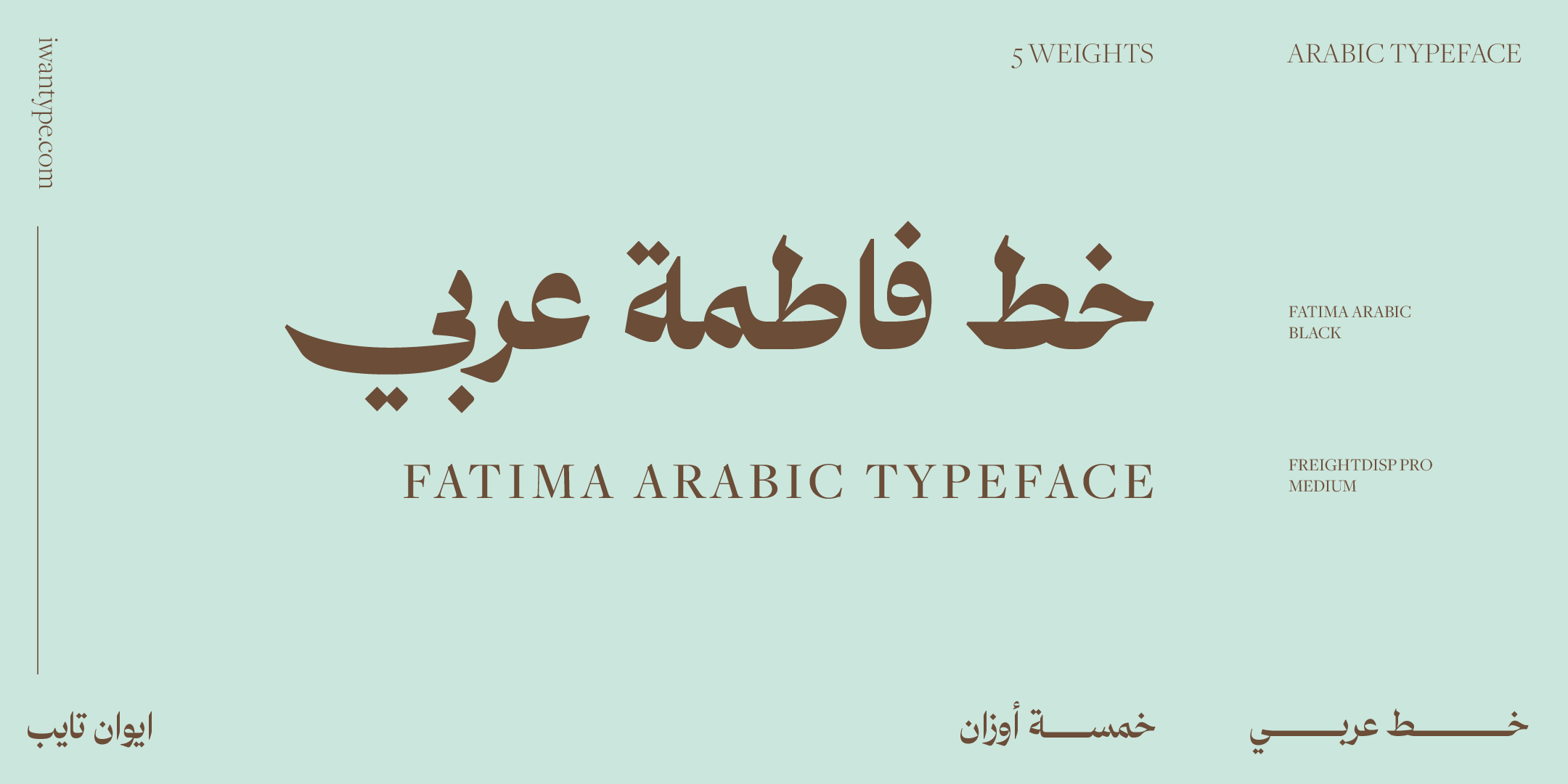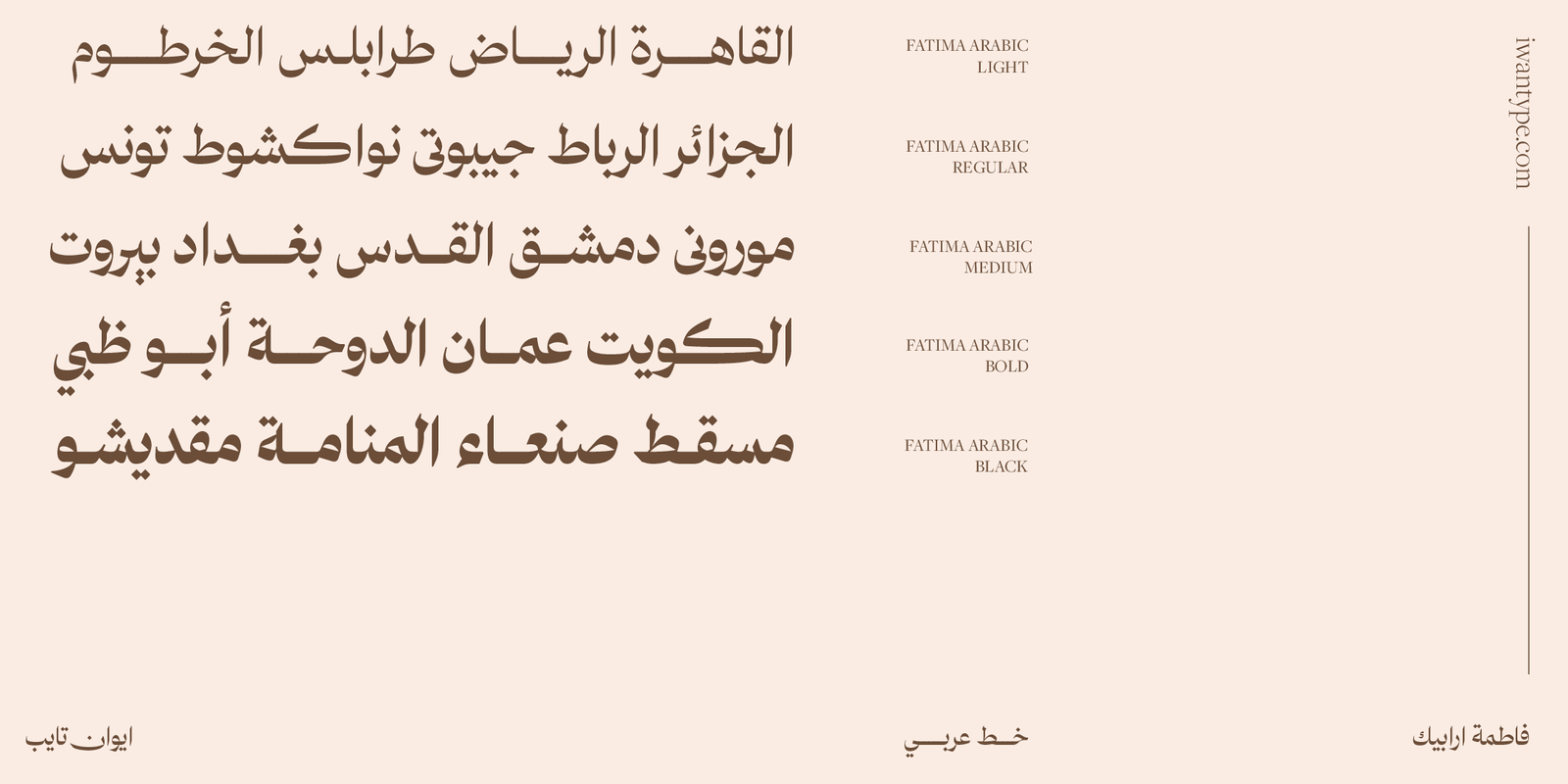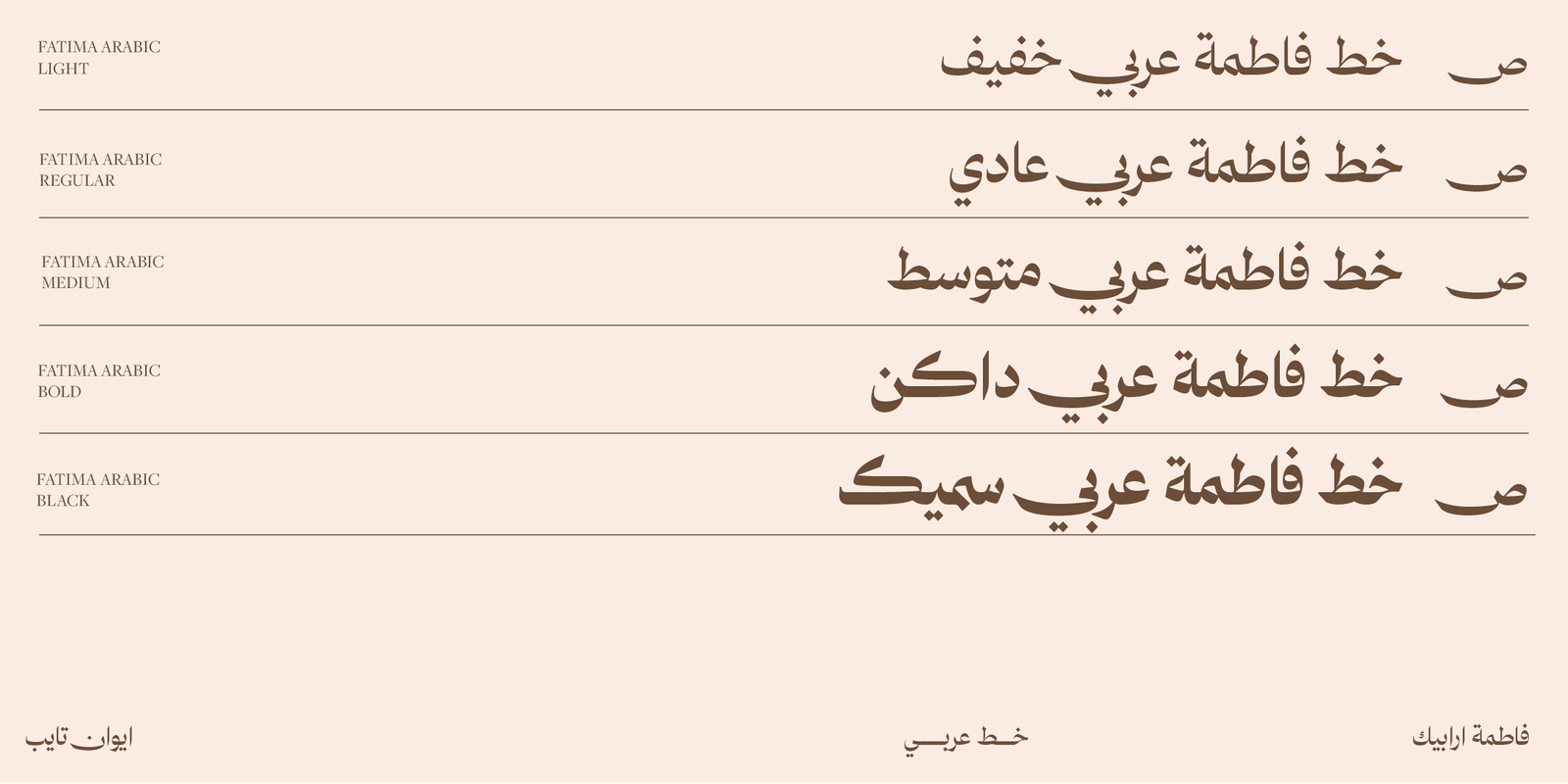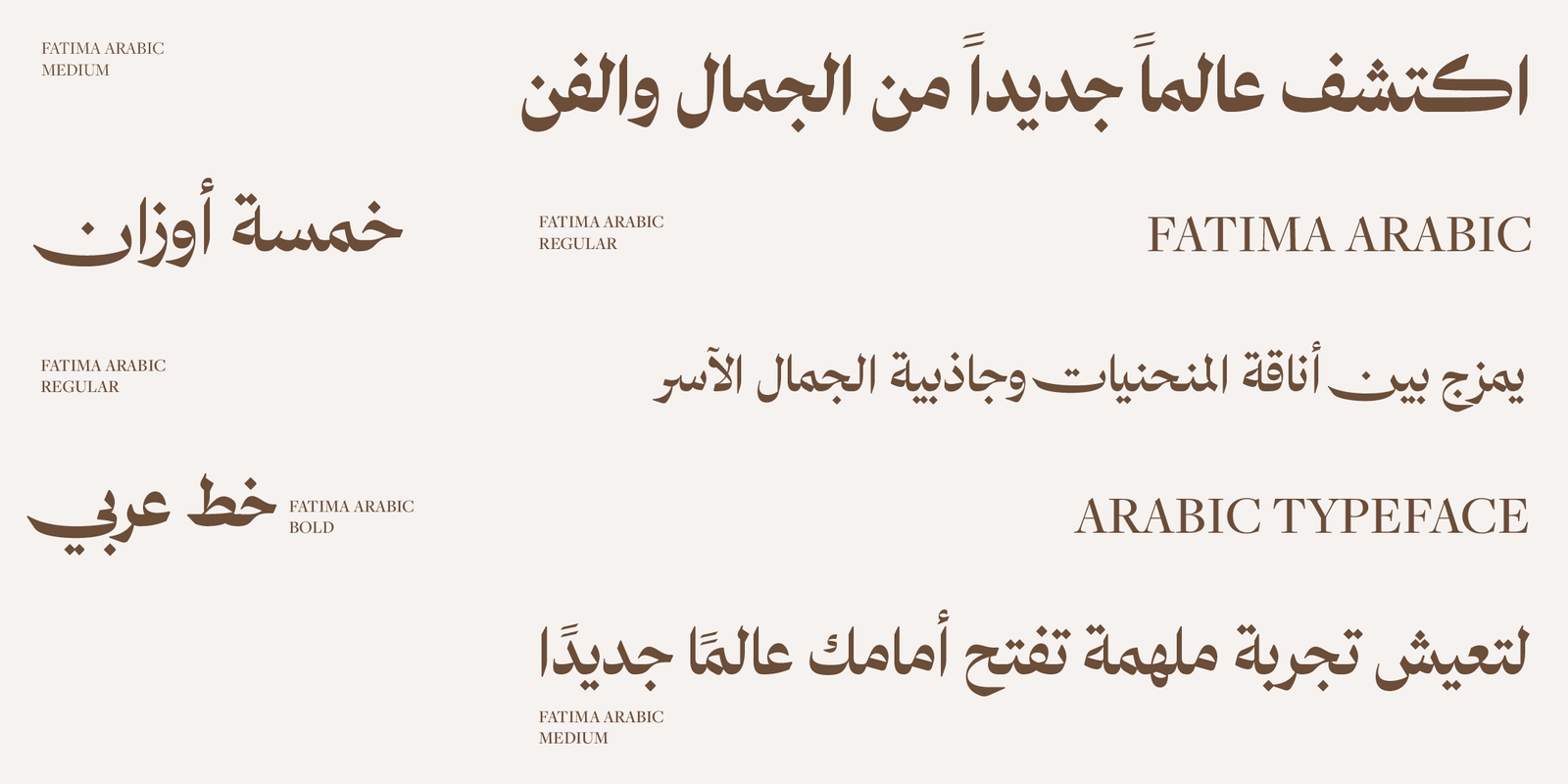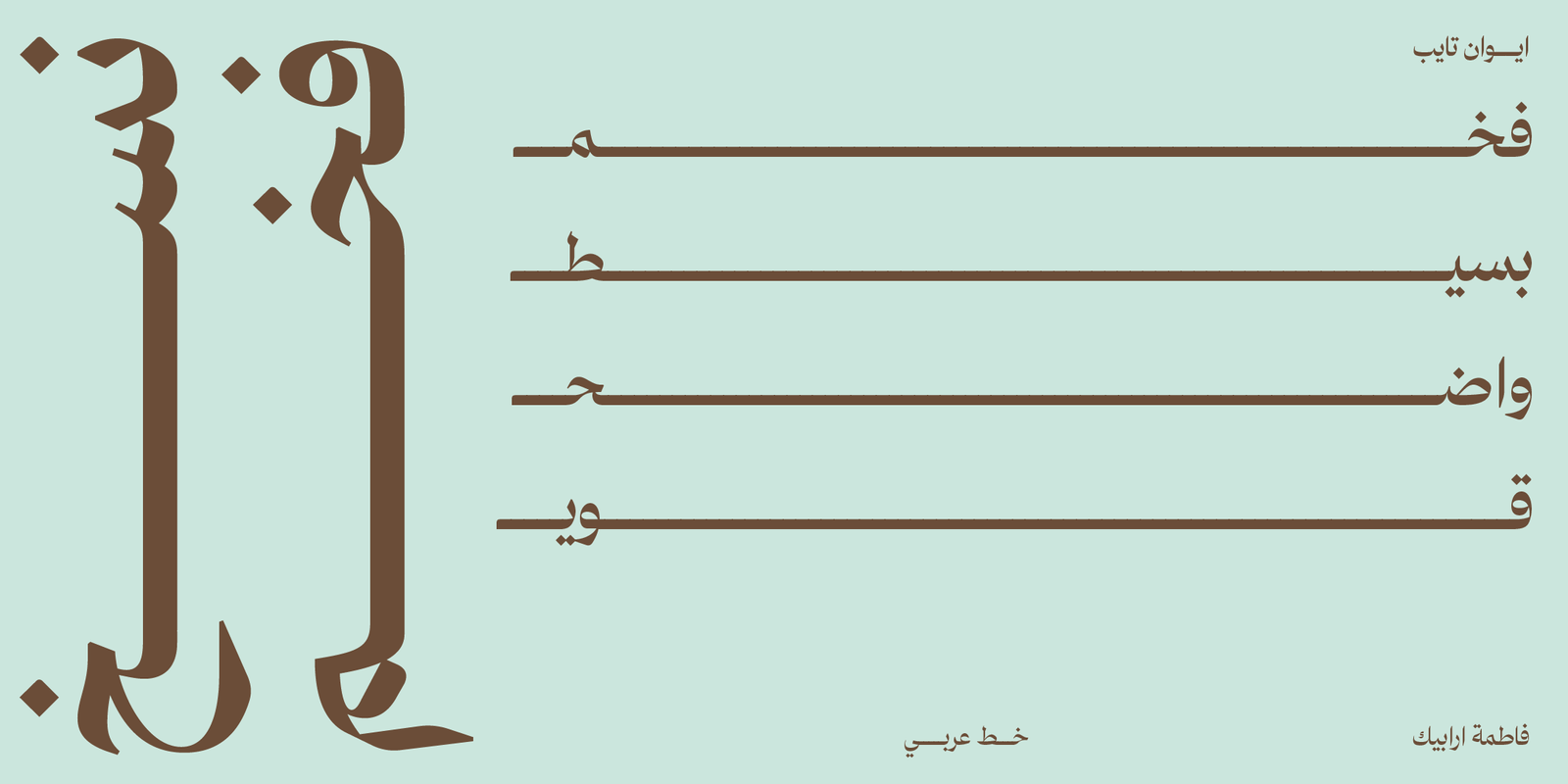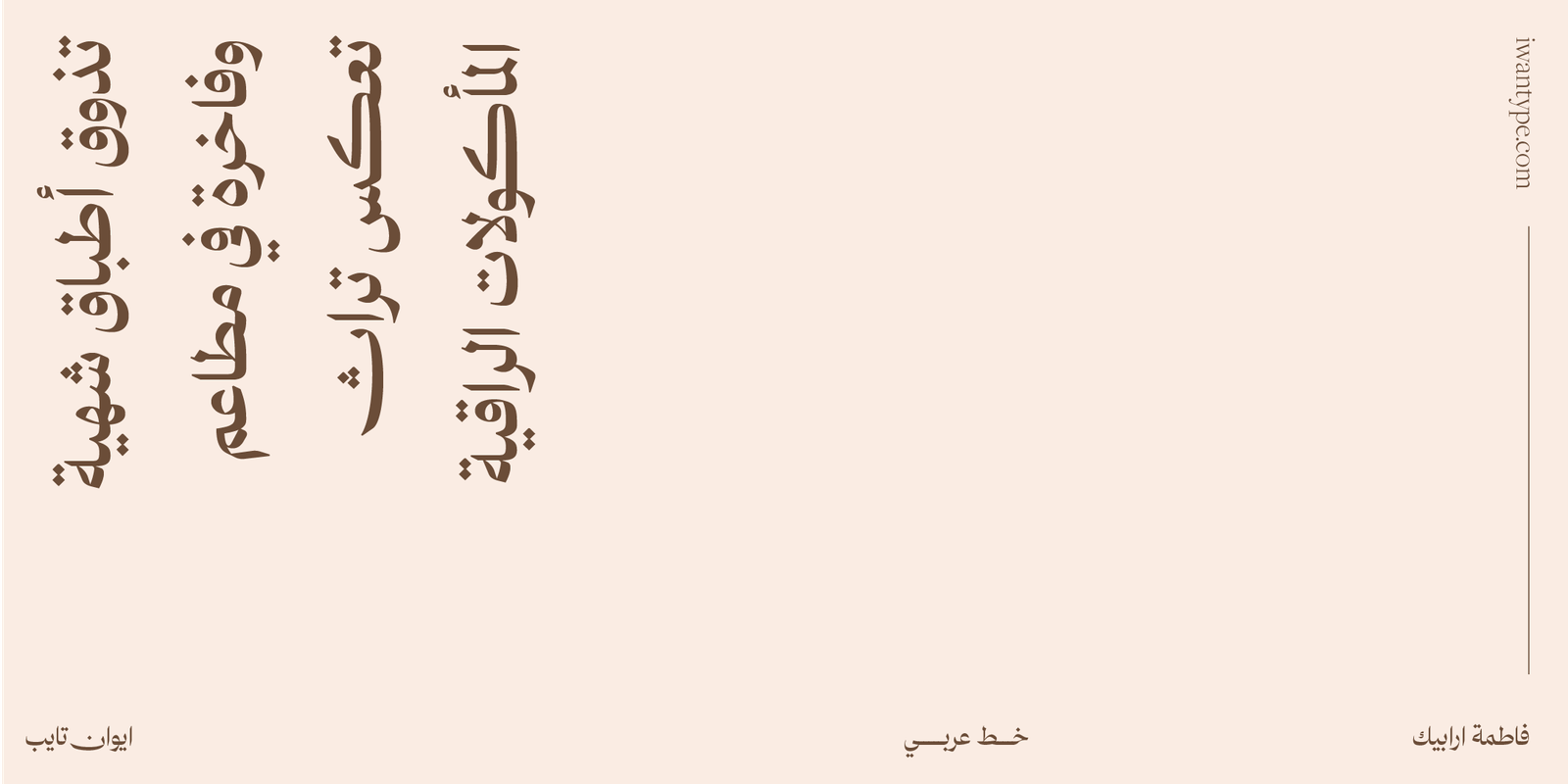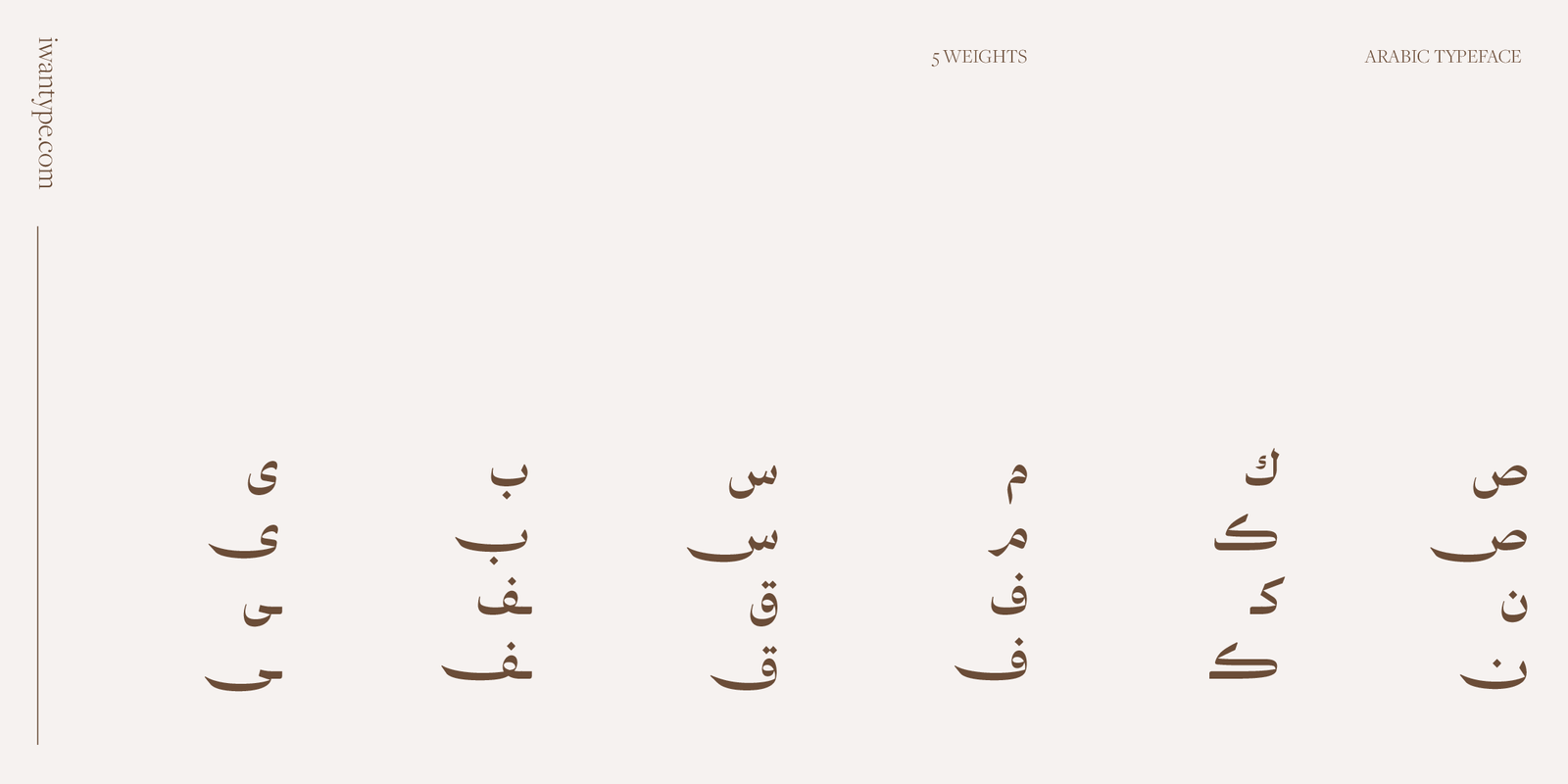
Fatima Arabic typeface – خط فاطمة عربي
فاطمة عربي هو خط طباعي عربي حديث يستلهم من أسلوب الخط النسخ، ويتميز بتباينه العالي ونسبه المتقنة.
يتميز هذا الخط بميزات متقدمة من نوع OpenType، تتضمن الحروف المركبة ومجموعات الأنماط، ويأتي بخمسة أوزان متنوعة،
بدءًا من الخفيف وصولاً إلى الأسود.
فاطمة عربي يعتبر خيارًا مثاليًا لمجموعة واسعة من الاستخدامات، سواء في الطباعة أو الوسائط الرقمية أو الشاشة.
إنه خط طباعي متعدد الاستخدامات يناسب كل من التطبيقات الرسمية وغير الرسمية.يتميز الخط بتباين واضح يمنحه مظهرًا حديثًا وأنيقًا.
يتمتع الخط بنسب متوازنة، مما يسهل قراءته واستخدامه.يتضمن ميزات متقدمة من نوع OpenType، مثل الحروف المركبة ومجموعات الأنماط،
مما يوفر للمستخدم خيارات إبداعية أكبر في استخدامه.
يأتي الخط بخمسة أوزان، بدءًا من الخفيف وصولاً إلى الأسود، مما يمنح المستخدم مرونة أكبر في اختيار الوزن الملائم لاحتياجاته.
الاوزان : خمسة اوزان
اللغات: العربية فقط، بلا حروف لاتينية